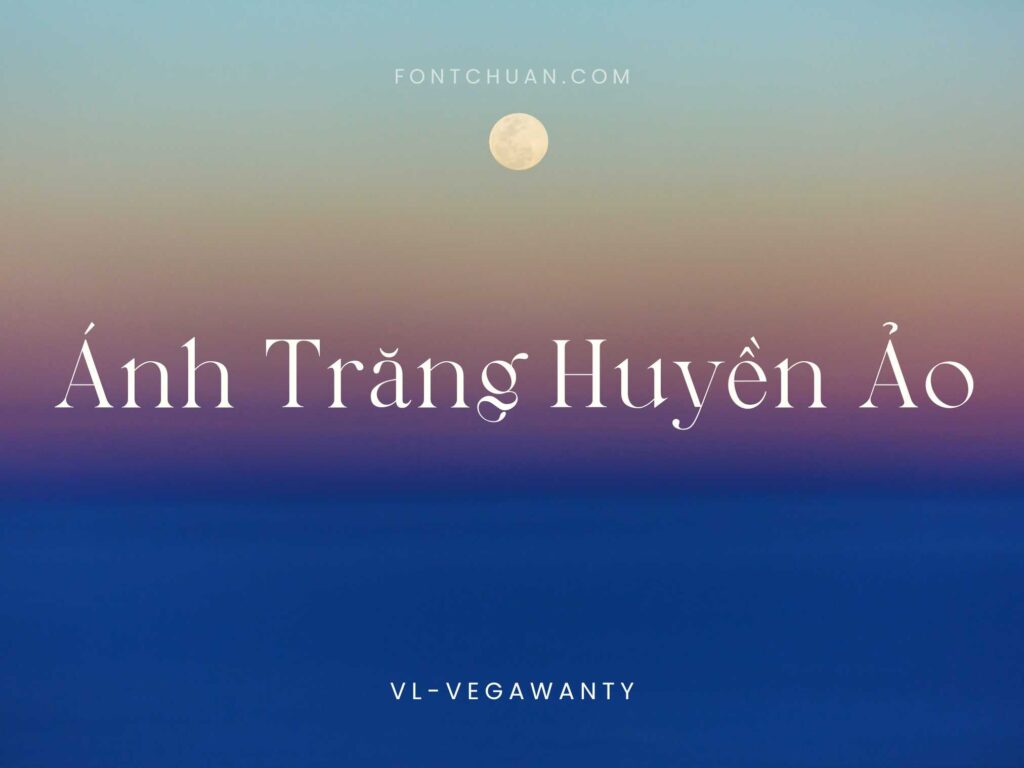
VL-Vegawanty là một phông chữ serif hiện đại, mang lại cảm giác sang trọng và tinh tế. Được thiết kế bởi Creatype Studio, phông chữ này phù hợp cho các dự án như thiết kế logo, thương hiệu, thiệp cưới, bài đăng trên mạng xã hội, quảng cáo, bao bì sản phẩm và nhiều ứng dụng khác. VL-Vegawanty đã được Việt hóa bởi Việt Linh, hỗ trợ đầy đủ các ký tự tiếng Việt, giúp người dùng dễ dàng áp dụng trong các dự án sáng tạo. Phông chữ này được thành viên Font Chuẩn sưu tầm và đăng tải nhằm phục vụ nhu cầu thiết kế đa dạng.
Với thiết kế thanh lịch và hiện đại, VL-Vegawanty phù hợp cho các ứng dụng như tiêu đề, logo, thiệp mời và các ấn phẩm in ấn. Trong lĩnh vực sự kiện, phông chữ này có thể được sử dụng trong các dịp như thiệp cưới, lễ hội và sinh nhật. Ngoài ra, VL-Vegawanty cũng thích hợp cho các ngành nghề như quảng cáo, giáo dục và công nghệ.